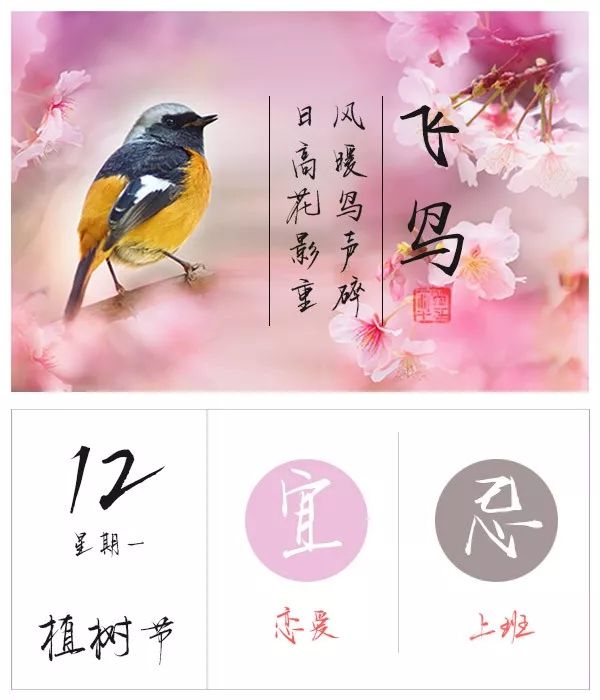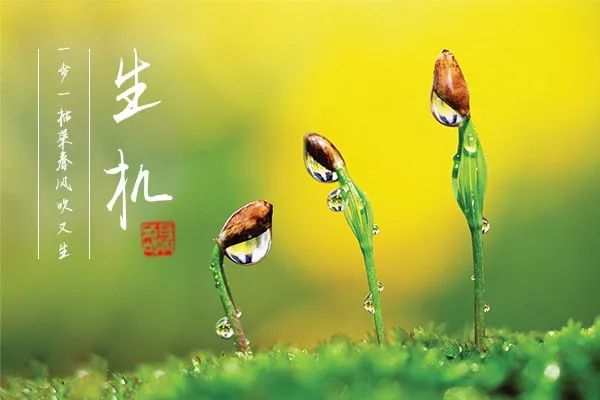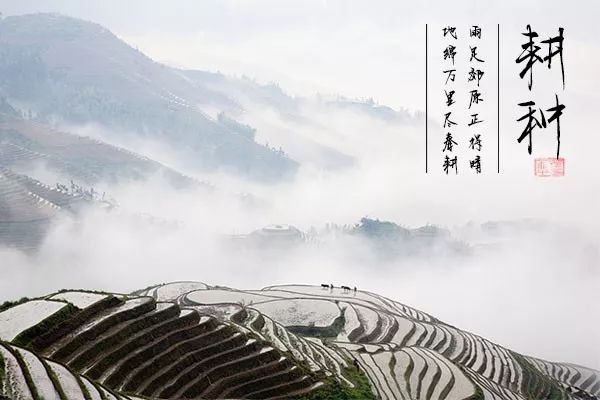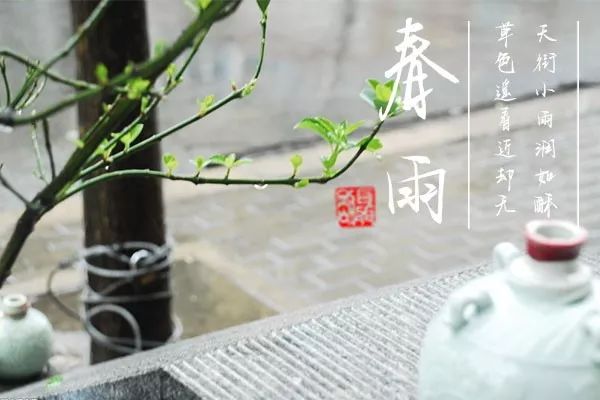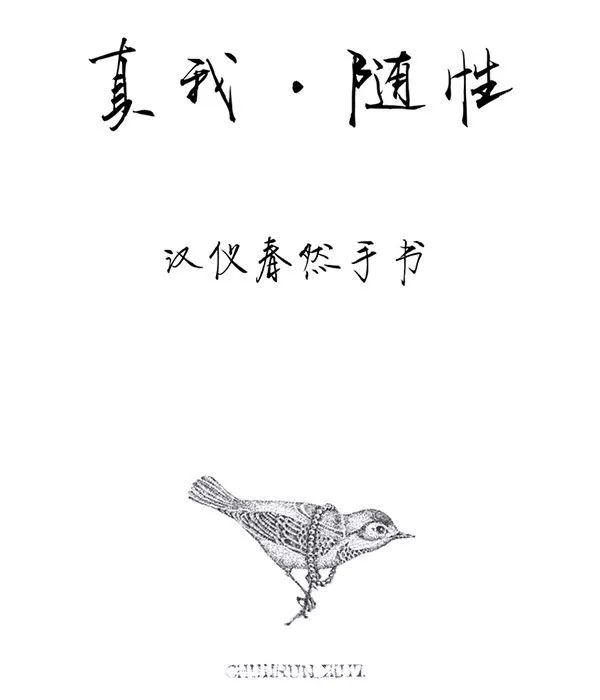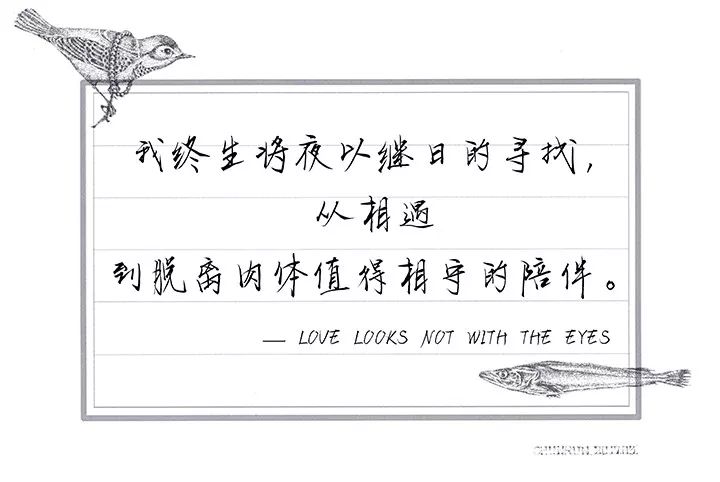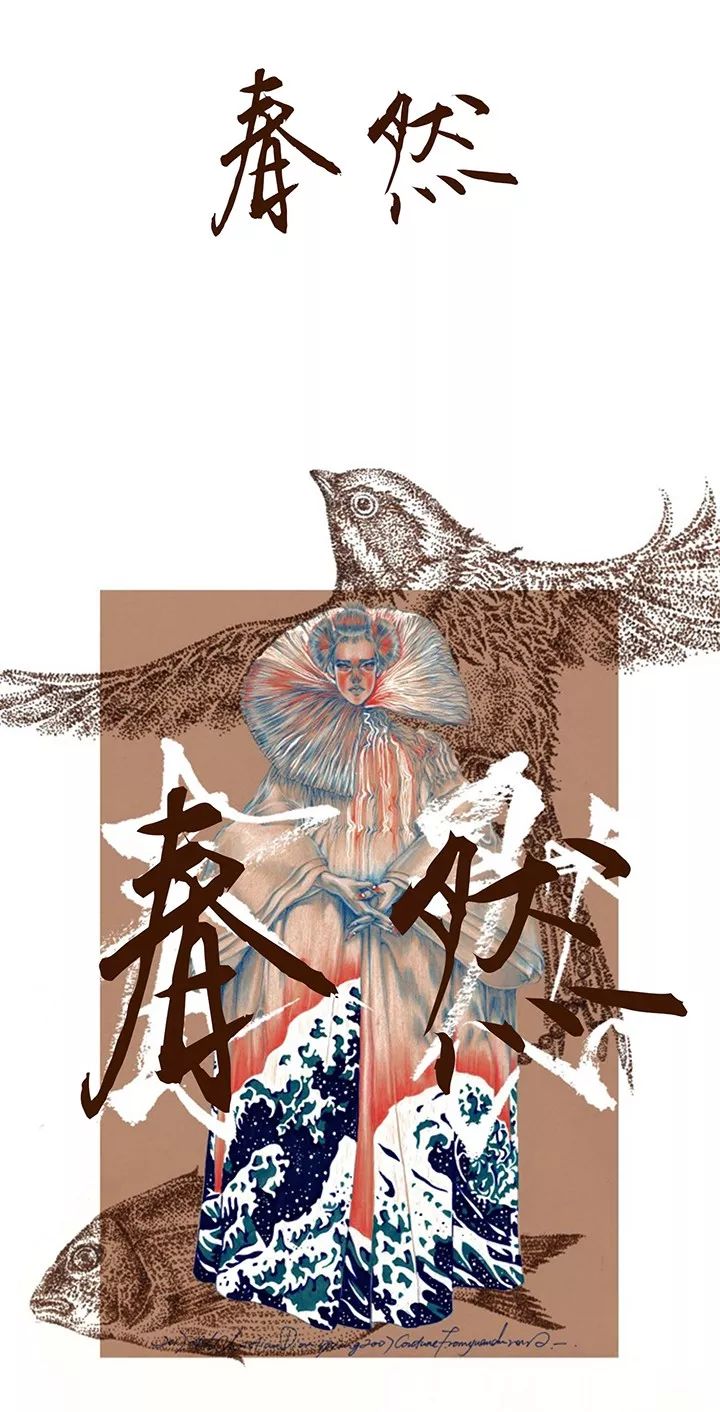
汉仪春然手书字体介绍,汉仪春然手书设计灵感,使用场景
盼望着,盼望着,东风来了,
春天的脚步近了。
一切都像刚睡醒的样子,欣欣然张开了眼。
---朱自清《春》
随着惊蛰的过去
春天的脚步离我们越来越近了
环顾四周
野花、树木、禾苗……
一切绿色仿佛都以可见的速度充盈起来
冬眠的动物也被温暖的大地唤醒
新一年的耕作也在此时悄然开始
对于生活在钢筋水泥森林的当代人而言
乡野的气息是如此的遥远
能唤醒人们对春天的记忆
唯有那淅沥沥的春雨
和藏在字由中的
汉仪春然手书
手写类字体更像是用字去说话
它有温度,有声音,有感情
尖锐肯定的笔画,清秀有力的字型
字里行间给人透露出一种青春洒脱之感
也许单纯的欣赏字体
还不足去展现它全部的美
那么
优秀的应用环境则使
字体的生命绽放
将字体融入设计
用恰当的手法去烘托
更能发现字体真正的美
>文艺类场景<
>古诗词类场景<
>运动休闲类场景<
更多优秀案例及场景
等待大家的挖掘